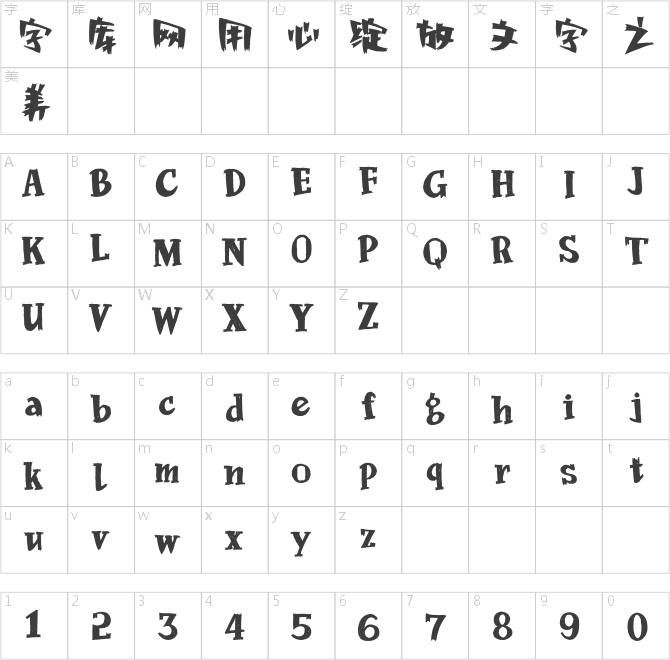
字体名称: 方正法小珂体简
方正法小珂体简
方正法小珂体简介绍
方正法小珂体,从字形来看并不规矩,如同长歪了的树,每个字都打破传统字形规范,重心右倾,左右上下各部分大小比例鲜明,却生出自有的平衡体系和风格,兼具笨拙 、直率、质朴、随性、懒散、童真,枯笔效果可能还带出一点飒。“任性的洒脱,克制的浪漫”,大概就是这样子吧。适用于独立,喜与众不同,文艺情怀爱好者,应用于标题,包装,海报,广告,文化印刷品及周边。
方正法小珂体简效果图